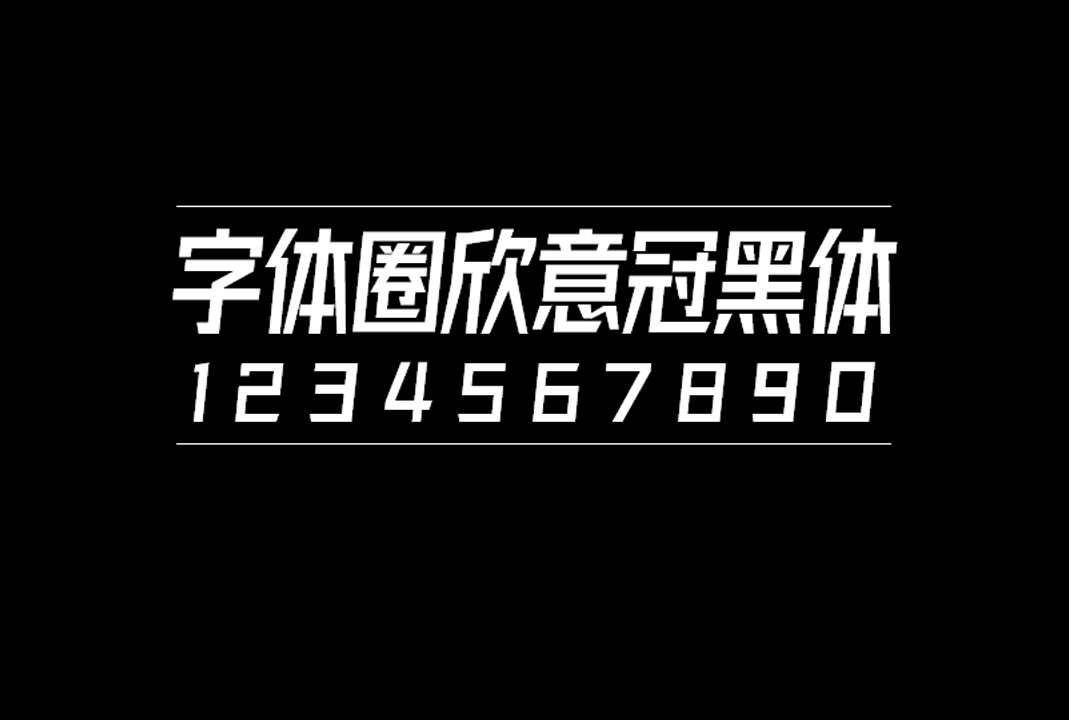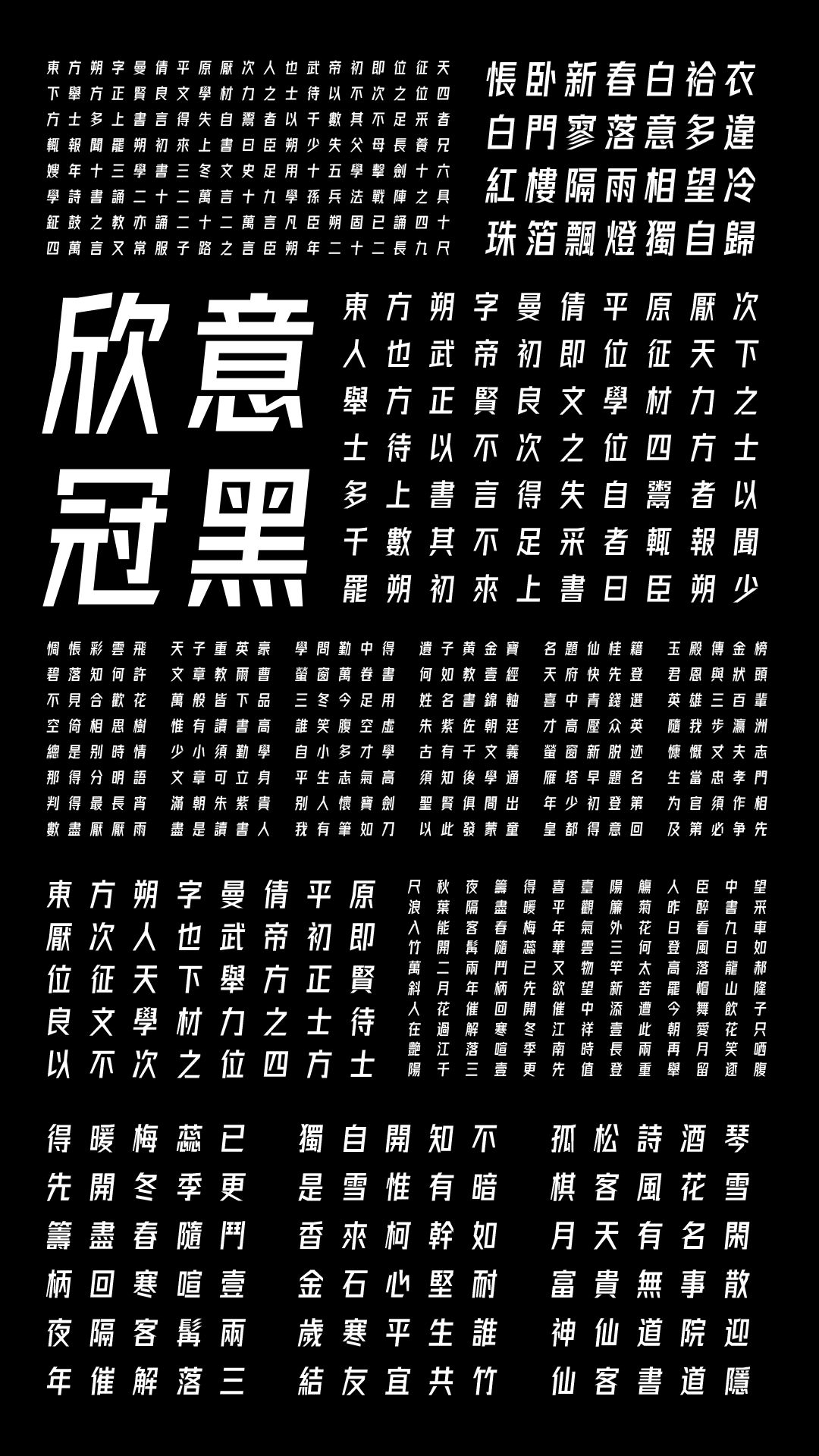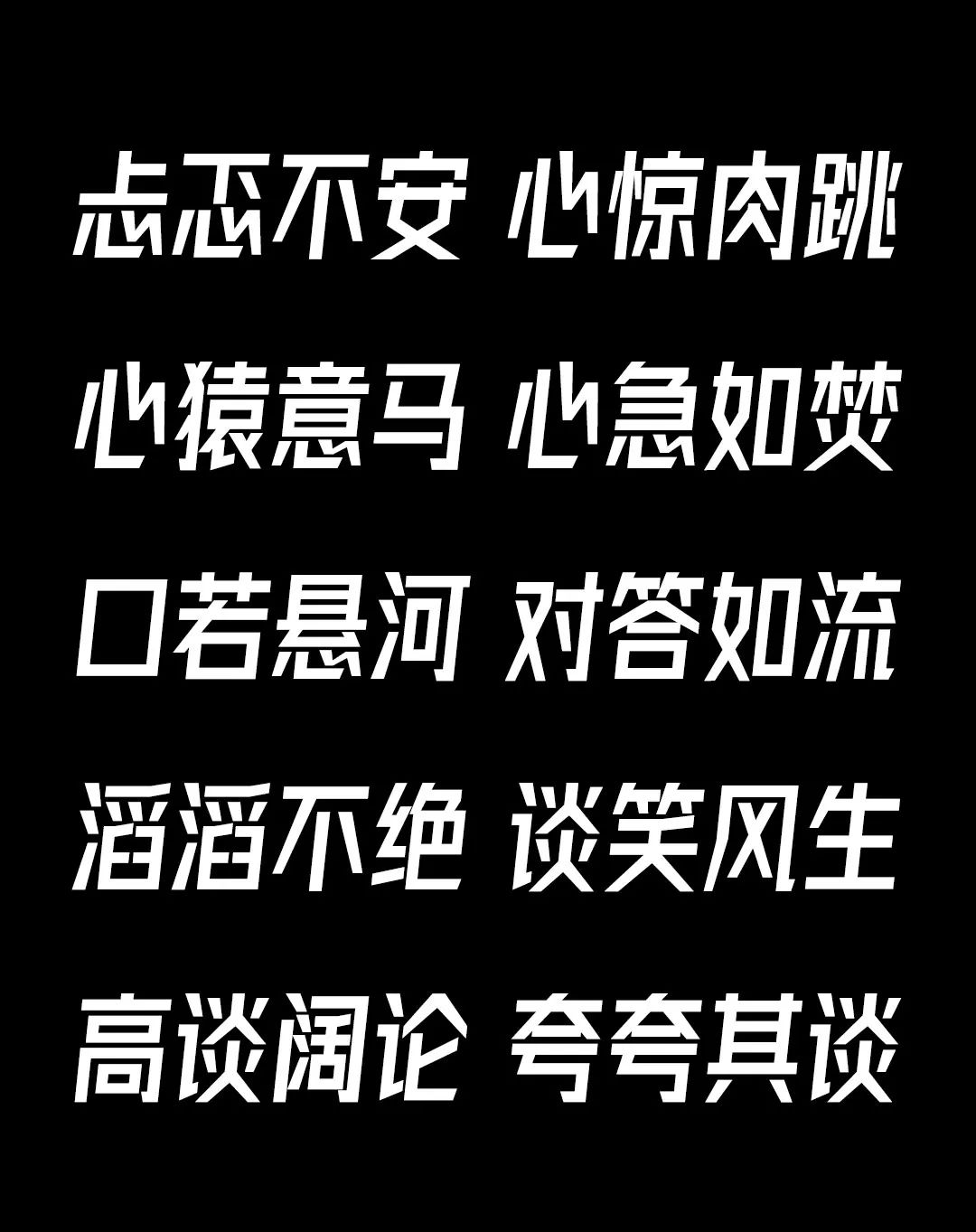
字体圈欣意冠黑体 | 中文免费商用字体下载
字体圈欣意冠黑体(V4.0)由邹乐伟于微信公众号字体圈(公众号ID:fontquan)发布的一款中文免费商用字体。
这套字涵盖国家 GB2312 标准的 6763 个中文字符,52 个英文字符,10 个阿拉伯数字,若干个中英文符号,按需添加若干个生僻字,共 7000 余字符。因为字形偏高瘦型,测试过这套字倾斜 8°有点奇怪,最后选择倾斜 6°,视觉平衡多了。